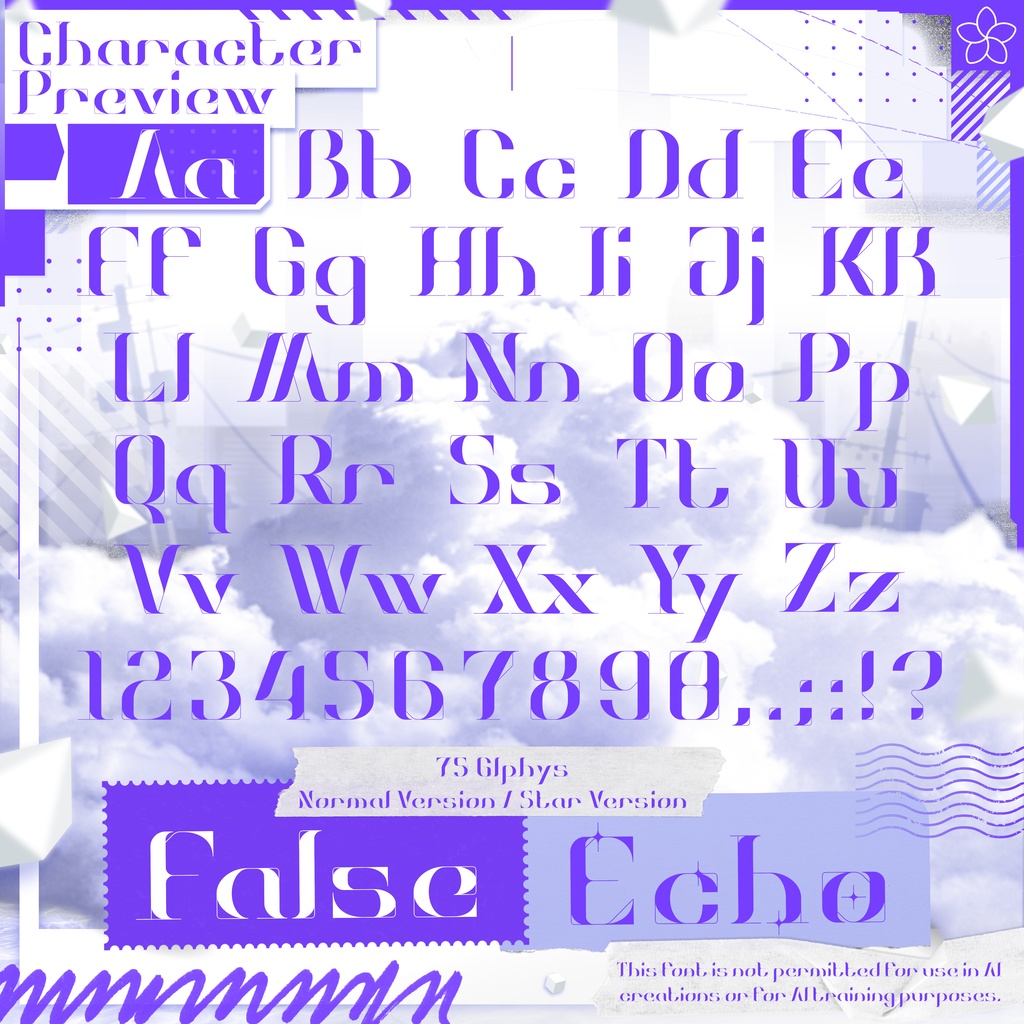
📢デザイン📢
ゴシック風フォントのような太い筆画と、極細の機械的なフレームが組み合わさり、感情表現力を持ちながらも未完成な印象を与え、想像の余地を与える。 宣伝画像はスクラップノートと崩壊したUI画面を無理やり組み合わせ、自然と文明の背景がフォントの二面性を再び示唆します。
📢內容📢
ラテン文字、句読点を合計で75グリフ、さらに2つのデザインスタイルが含まれています。